La Voie Des Oubliés.
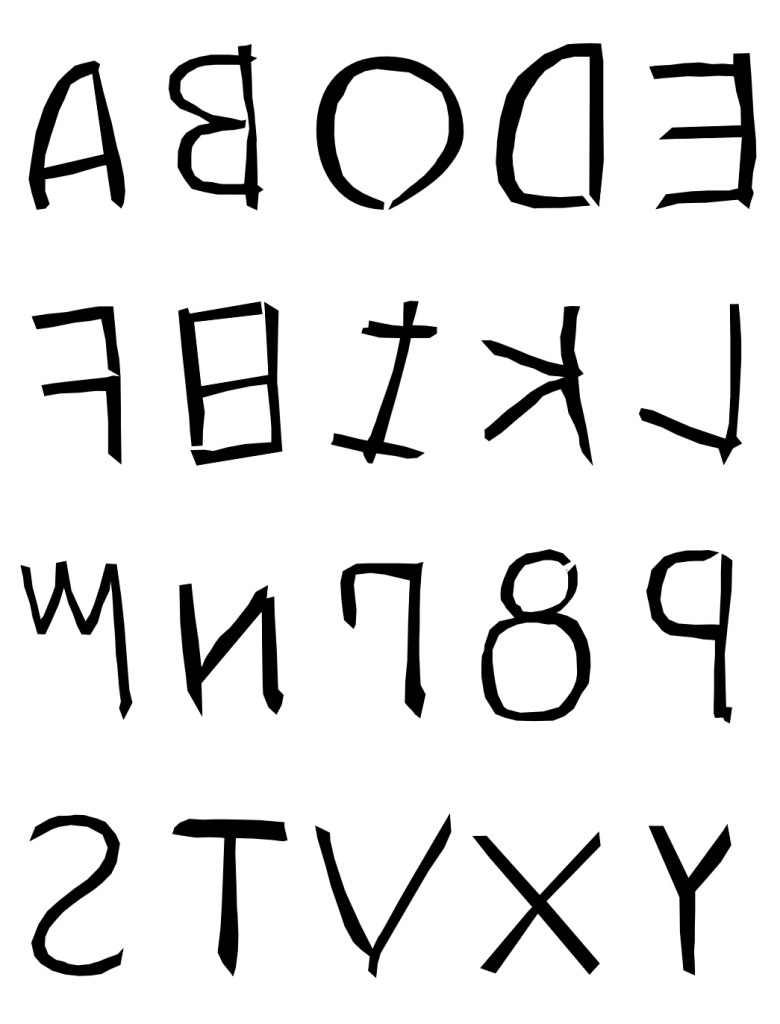
Les origines du Latin sont Grecques, c’est la filiation officielle telle qu’elle fut présentée par les grands auteurs. Pourtant nous allons consacrer un petit temps de réflexion à une variante intermédiaire de l’alphabet, qui précéda puis coexista avec le Latin.
Nous ne savons pas assez de choses sur ces prédécesseurs qui vivaient dans les régions nord et centrale de la Péninsule Latine, un territoire que l’on nomme encore l’Étrurie.
Que l’on suive la voie historique, écrite en Latin, ou que l’on réfléchisse aux interactions économiques et sociales entre les deux peuples, tout concourt à indiquer que les descendants de Romulus sont en grande partie des Étrusques.
Histoire des Origines
L’écriture des Étrusques est n’a pas survécu, pas plus que leurs histoires. Avaient-ils des raisons de vouloir s’absorber dans une légende plus grande, en échange d’un partage du pouvoir ?
Nous ne disposons que de quelques exemples de leur écriture, un niveau de rareté suspect. La comparaison avec le Latin archaïque est troublante puisque l’alphabet semble avoir été inversé.
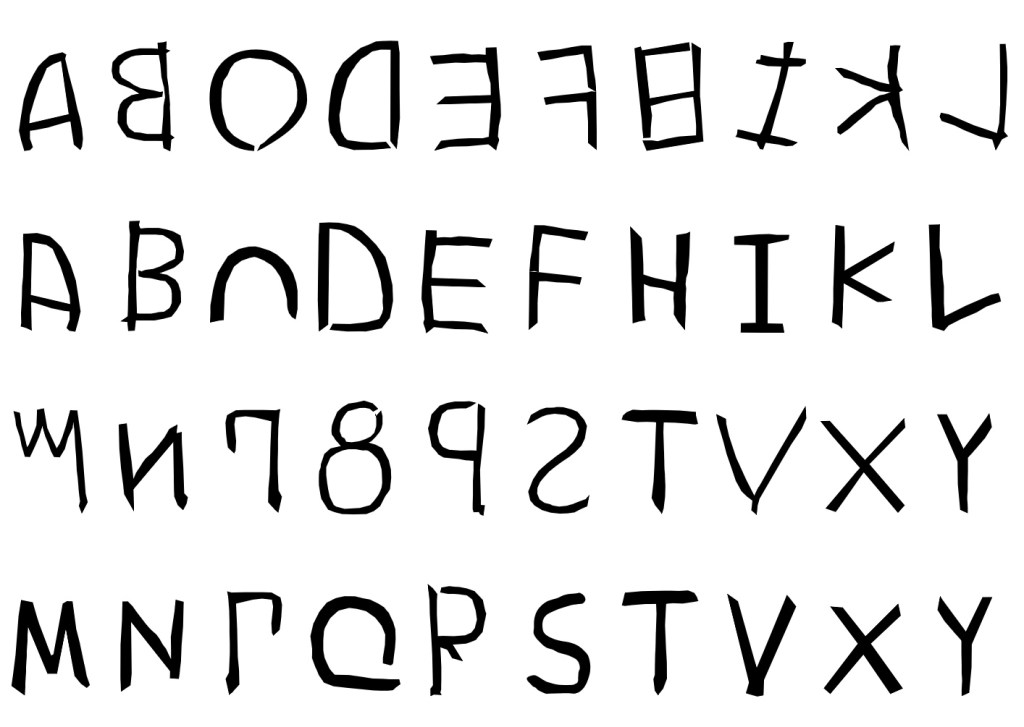
En observant les bribes qui ont échappé à l’effacement, nous observons une écriture proche du Latin archaïque, nous pourrions penser que l’une se présente en miroir de l’autre.
C’est à peu près tout. Les compétences artistiques et économiques Étrusques sont mal connues. On sait toutefois qu’elles étaient développées et influentes sur une bonne partie du Bassin Méditerranéen.
La formation des caractères
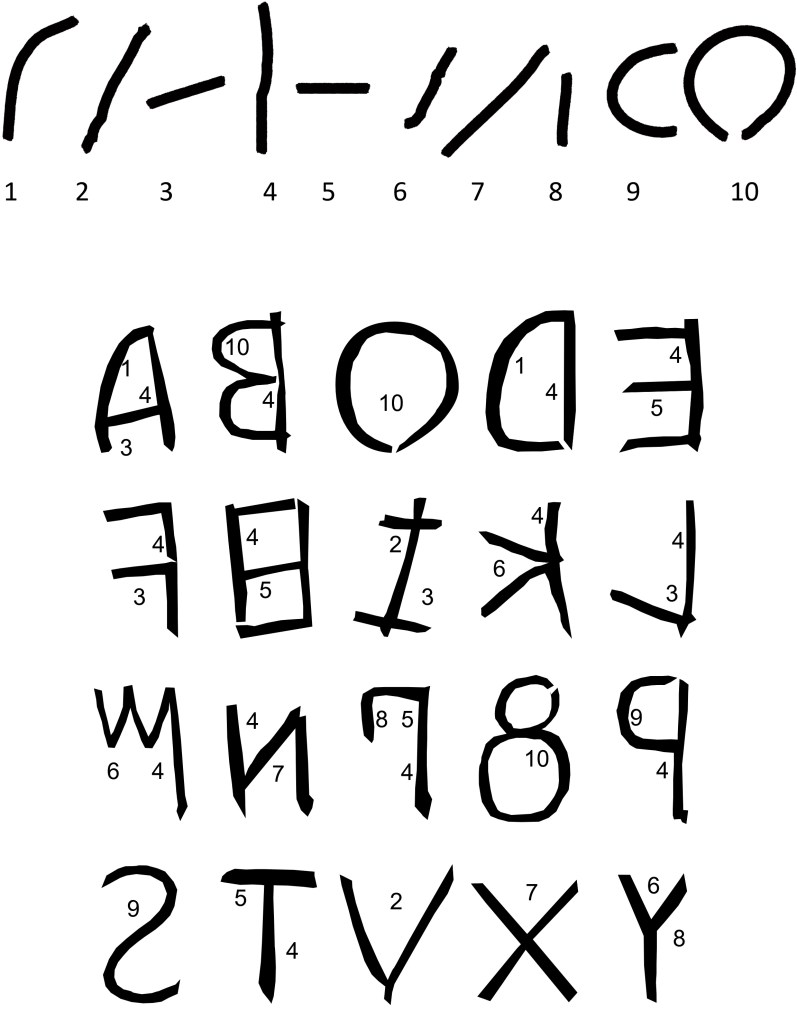
Nous avons là un quasi copié collé en miroir depuis le Latin Archaïque.
Avec toutefois des différences assez flagrantes au niveau des lettres C, un quasi cercle chez les Etrusques et Q qui ressemble à un 8 avec une petite tête. Deux formes qui se retrouvent à l’identique en Phénicien.
L’équivalent du H est là aussi tellement proche de son homologue Phénicien que l’on peut supposer que l’étape Grecque n’a pas été influente L’alphabet Etrusque serait alors plus proche d’un crypto-Grec que du Ionique si bien léché. Aussi, il ne semble pas que, du fait de la présence d’autant d’arrondis, cette écriture ait été appliquée aux matériaux les plus durs.
Si les liens avec les Grecs étaient puissants, c’est toutefois la comparaison entre l’Etrusque et le Phénicien qui nous donne une majorité de lettres identiques.
Sur le plan politique, on se souviendra que le départ forcé du dernier roi Etrusque de Rome provoqua l’avènement de la République, laquelle n’eut de cesse que de faire tomber l’influence des Phéniciens.
En juxtaposant l’Étrusque avec le Grec archaïque, la parenté est visible, sans plus, contrairement au Latin archaïque. Cela peut être du au sens d’écriture, mais aussi à ce que les formations des deux séries de caractères sont simultanés, toutes deux héritières directes du Phénicien.
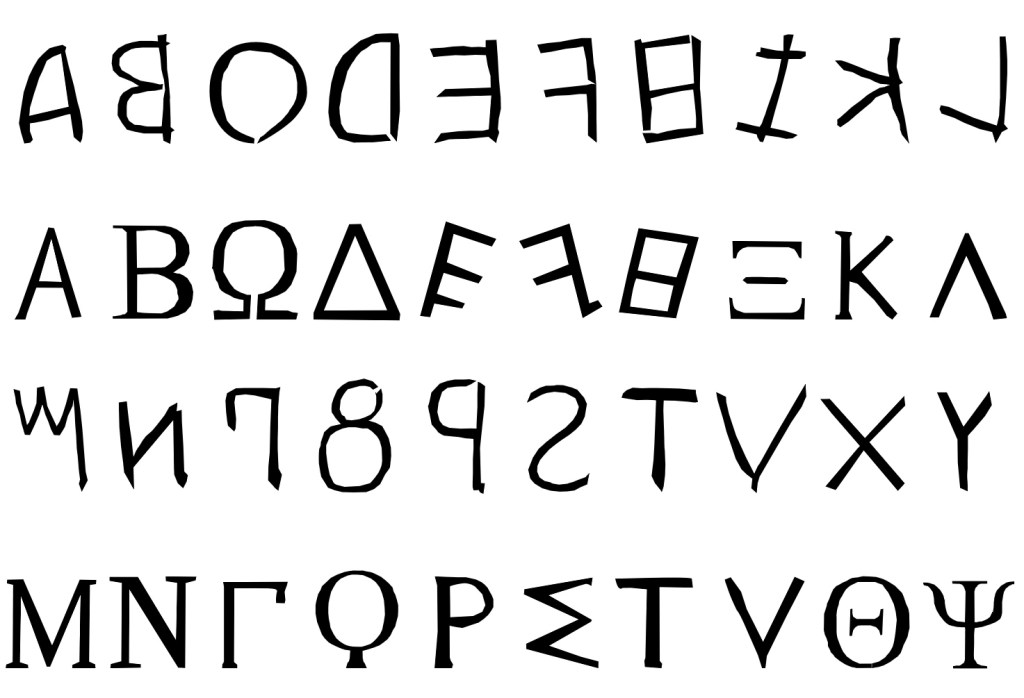
Sa place dans la culture de l’écrit
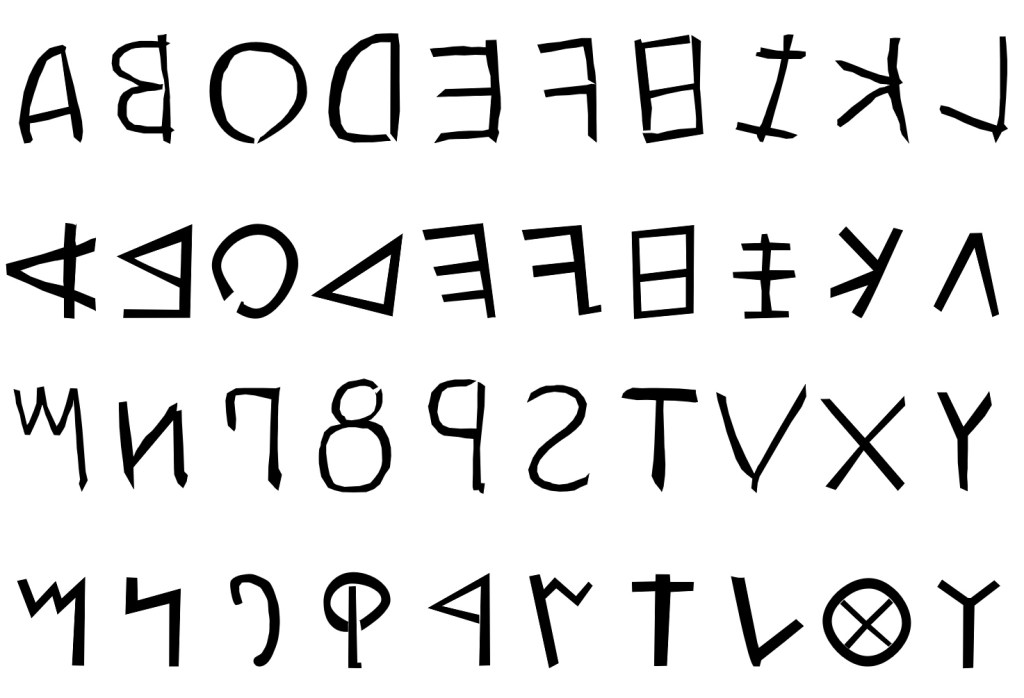
La comparaison directe avec le Phénicien est alors très instructive, car nous trouvons des graphies similaires pour la plupart des lettres et une orientation identique pour la quasi totalité, à l’exception comme si les Phéniciens avaient appris à écrire à des Étrusques très attentifs, mais enclins à arrondir les traits.